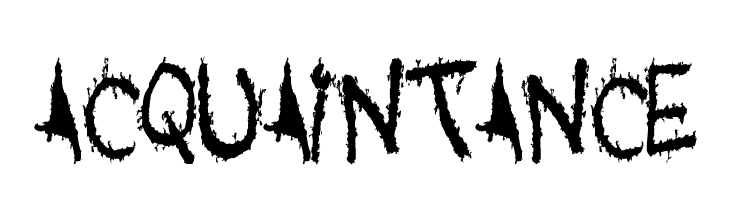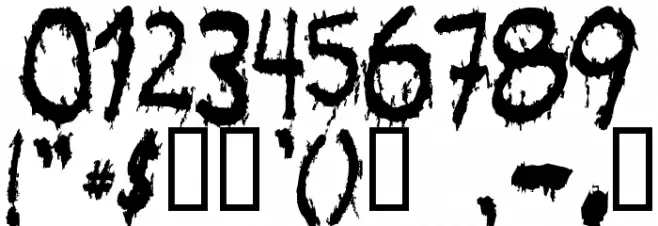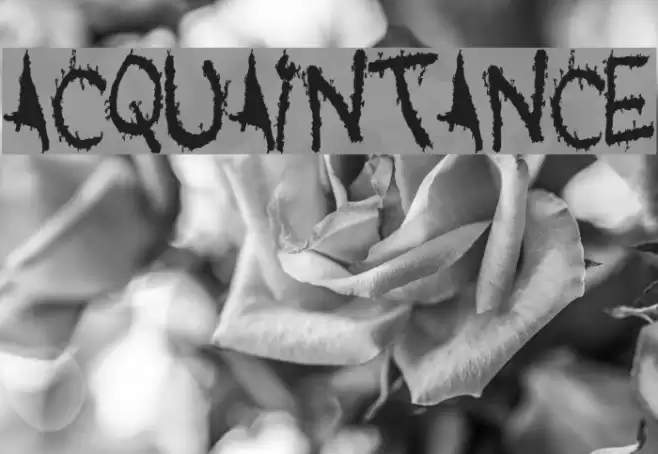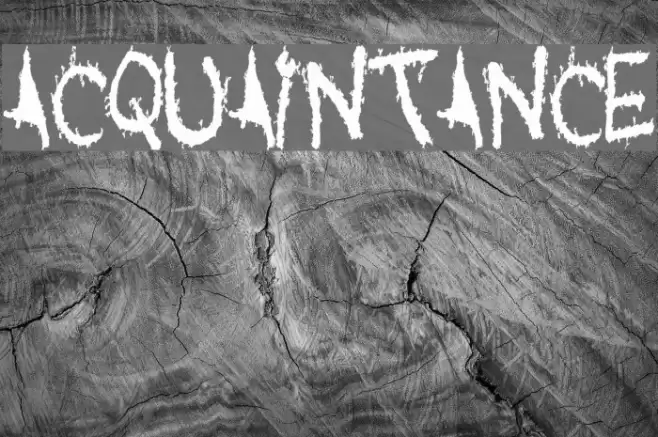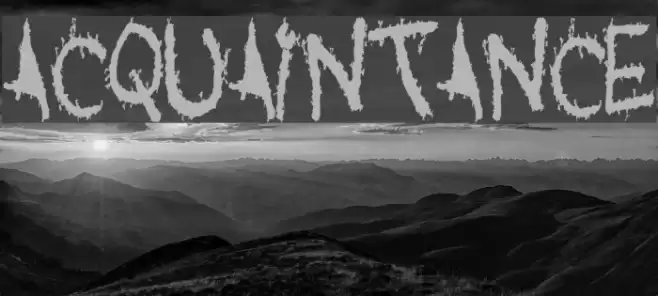
Acquaintance Font
| Vorgeschlagene Projekte | Ideal for posters, album covers, Halloween-themed designs, or any project requiring a bold, eye-catching typeface. |